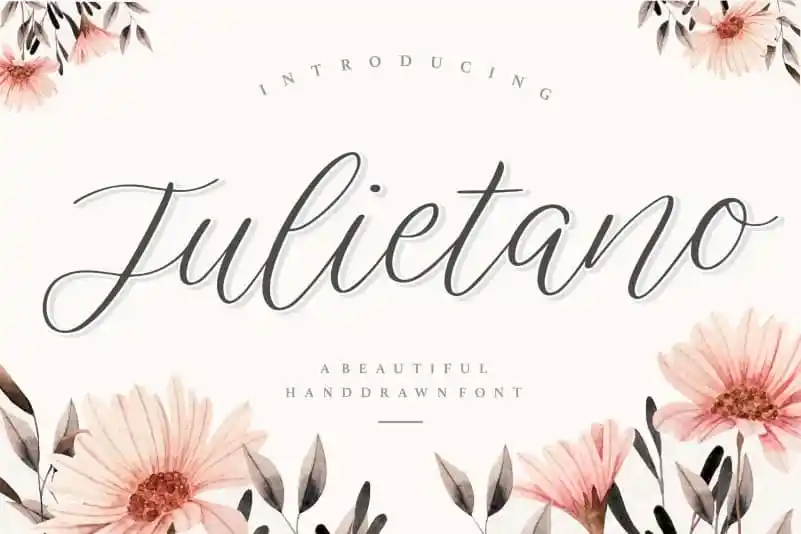
Julietano Handdraw Font – Download Grátis
A fonte ‘Julietano Handdraw Font’ é perfeitamente adequada para aplicativos visuais diversos no mundo digital, especialmente projetos criativos que valorizam uma mão-douriada e artesanal. Seja para embalagens de produtos, campanhas de marca, revistas, redes sociais, ou até mesmo para destacar mensagens em backgrounds mais sutis durante festas nupciais, esta fonte oferece um estilo delicado e envolvente que ajuda a realçar o olhar. Suave e personalizado, ela é uma escolha ideal para quem busca expressar emoções ou ideias de maneira única e reconhecível. Seja você um designer gráfico iniciante ou experiente, Julietano Handdraw Font certamente se encaixa perfeitamente em sua paleta de ferramentas, oferecendo o toque final necessário para suas projetos digitais.